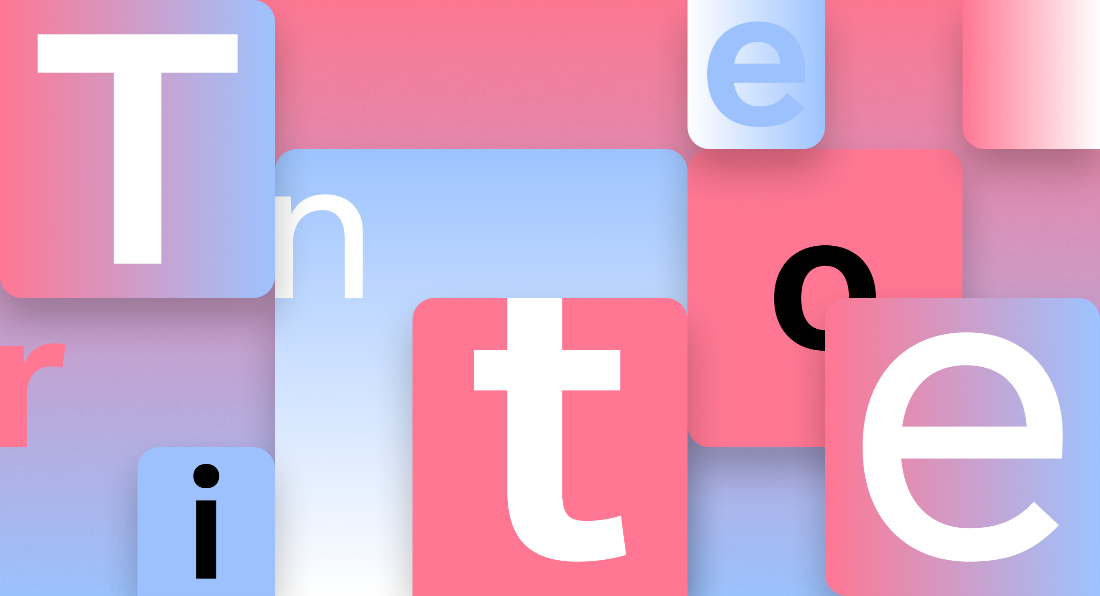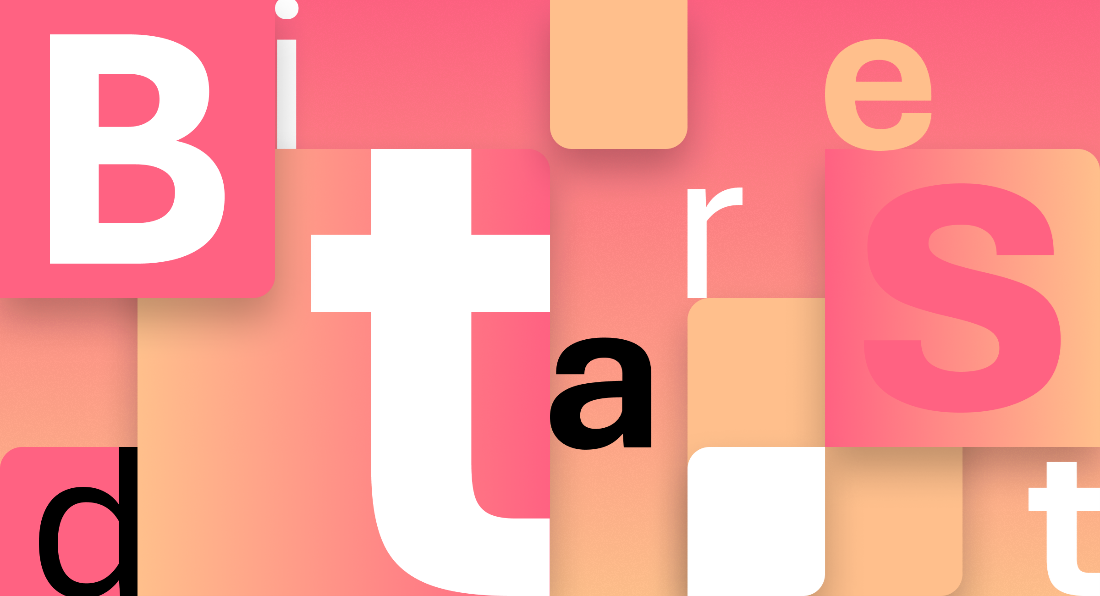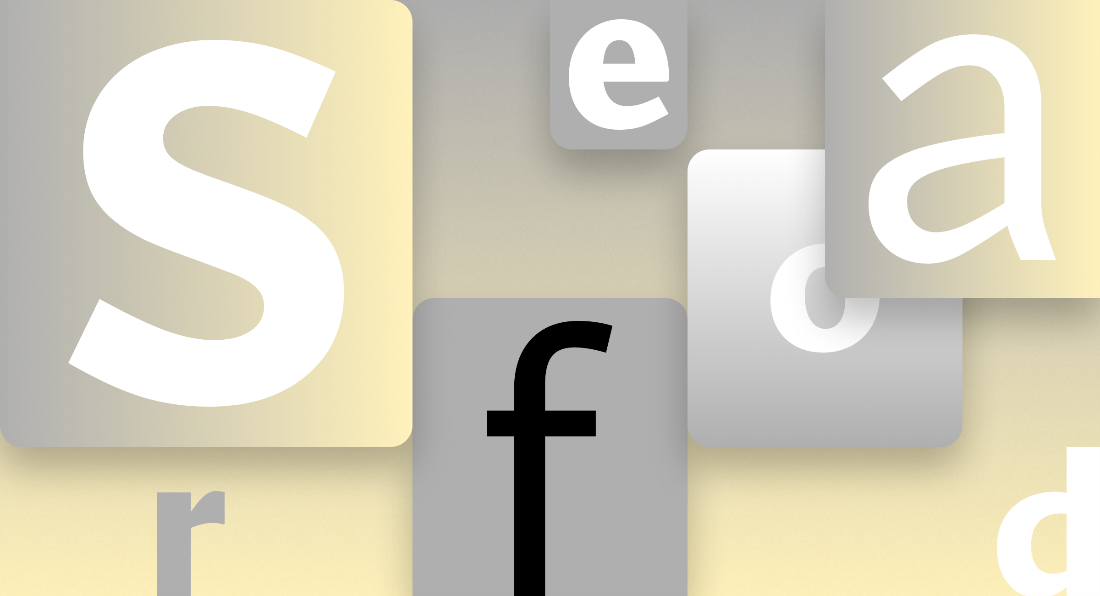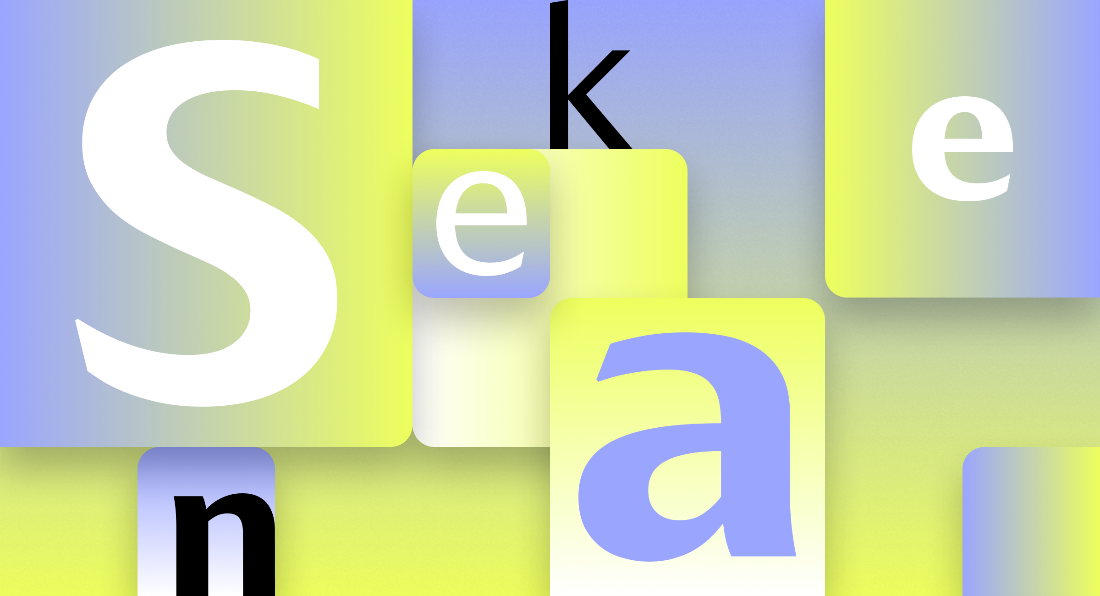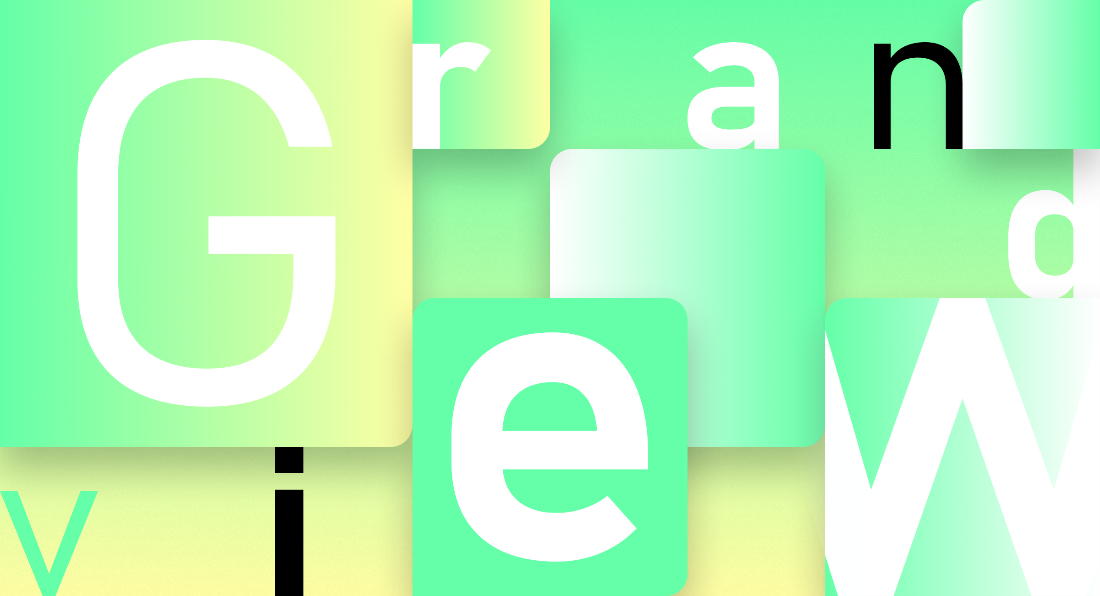
Microsoft предложила пользователям Office выбрать новый шрифт по умолчанию
В последний раз компания меняла его 14 лет назад
Компания Microsoft решила изменить шрифт по умолчанию в своем текстовом редакторе Office. С 2007 года им является Calibri. Ему предшествовал хорошо всем знакомый Times New Roman.
Теперь пользователи Microsoft Office могут сами выбрать новый шрифт. Им предлагается пять вариантов — наиболее традиционный Tenorite, одним из ориентиров для которого стал Trade Gothic, универсальный Bierstadt, вдохновленный швейцарской типографикой середины XX века, «гуманистический» Skeena, идеально подходящий для больших по объему документов, «комфортный» Seaford и Grandview с заимствованиями из классических немецких дорожных и железнодорожных указателей. Проголосовать за понравившийся нужно в твиттере.
«Шрифты по умолчанию, пожалуй, наиболее примечательны тем, что не производят никакого впечатления. Мы редко задумываемся о них, и в этом их величайшее достоинство. Когда шрифт сливается с пользовательским опытом, люди могут сразу переходить к творческому процессу и сосредоточиться на своих мыслях, не думая о форме, которую принимают эти мысли», — отмечается в заявлении Microsoft.